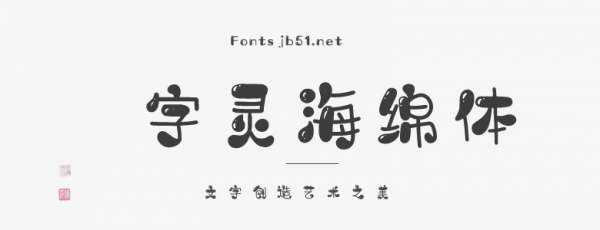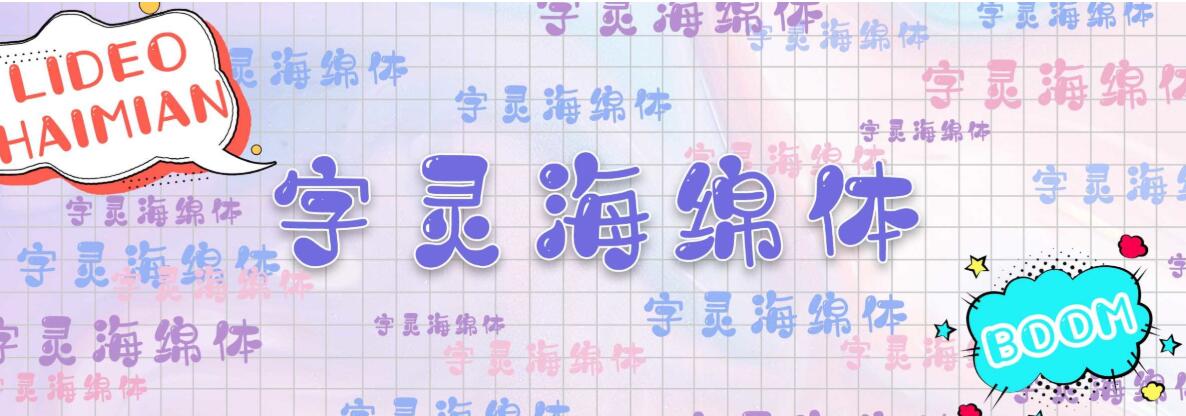
這款字靈海綿體是一款卡通可愛的創(chuàng)意字體。字體筆畫在點、撇、捺、橫、豎等筆畫中不同程度的增加了可愛的裝飾氛圍,字體的整體趣味性提高,給人帶來一種俏皮可愛的親切感。并在裝飾的同時,加入了高光的設計處理。使得字體似乎賦予了靈氣和生命力。
字靈海綿體字體轉折處呈現(xiàn)圓角,點筆畫呈不規(guī)則的水滴點狀,筆畫粗細大小對比明顯,且沒有尖銳的尖角和直線。字的造型自然有趣又不失可愛,令人印象深刻。
字體結構變化豐富且耐看,加強了字的個性和視覺沖擊力,圓潤線條之間的粗細變化提高了手寫感,字體顯得更加俏皮可愛,使字體個性更加鮮明。筆畫均衡分布、重心平穩(wěn),筆畫之間具有內在的呼應關系,起收有序、直而不僵、彎而不弱,字與字排列在一起時大小勻稱、行款整齊、流暢自然。